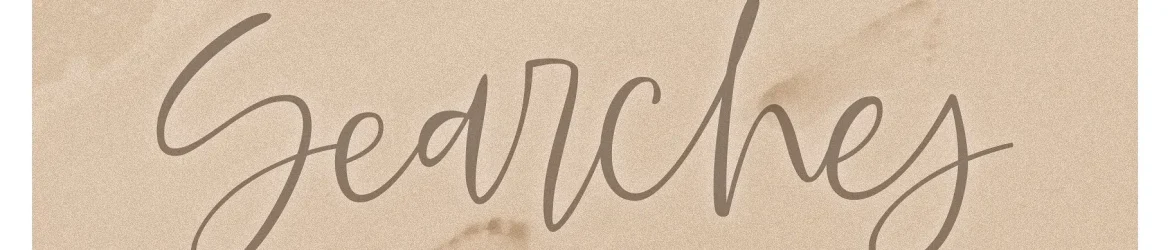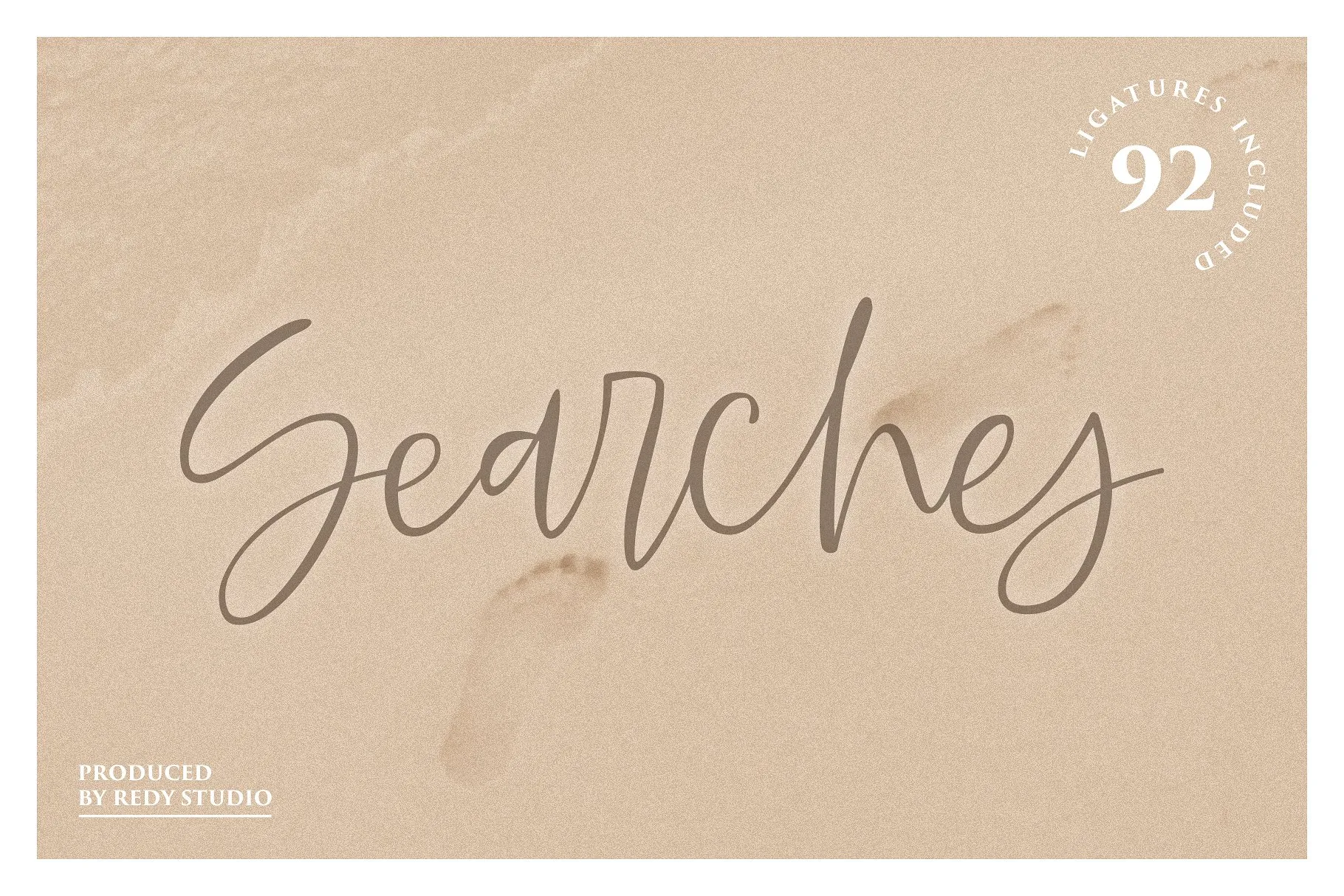
Searches Handwritten Font – Fonte Grátis
Searches Handwritten Font
Olá! Introduzimos a fonte Searches Handwritten Font do designer M.0Type. Essa fonte é uma mistura aparentemente desorganizada e exuberante, composta de 92 ligaturas, números, sinais de pontuação e alternativas, tornando-a perfeitamente adaptável para diversas necessidades. Ideal tanto para cartões de agradecimento, como materiais de marca ou cartão de negócios, também é uma escolha ótima para criações de logotipos, blogs, embalagens, marketing e revistas. Esta fonte traz um toque autêntico que pode tornar suas idéias ainda mais memoráveis em vários tipos de projetos visuais. Sem dúvida, a Searches Handwritten Font é uma adição inestimável para qualquer designista ou criador de conteúdo digital.